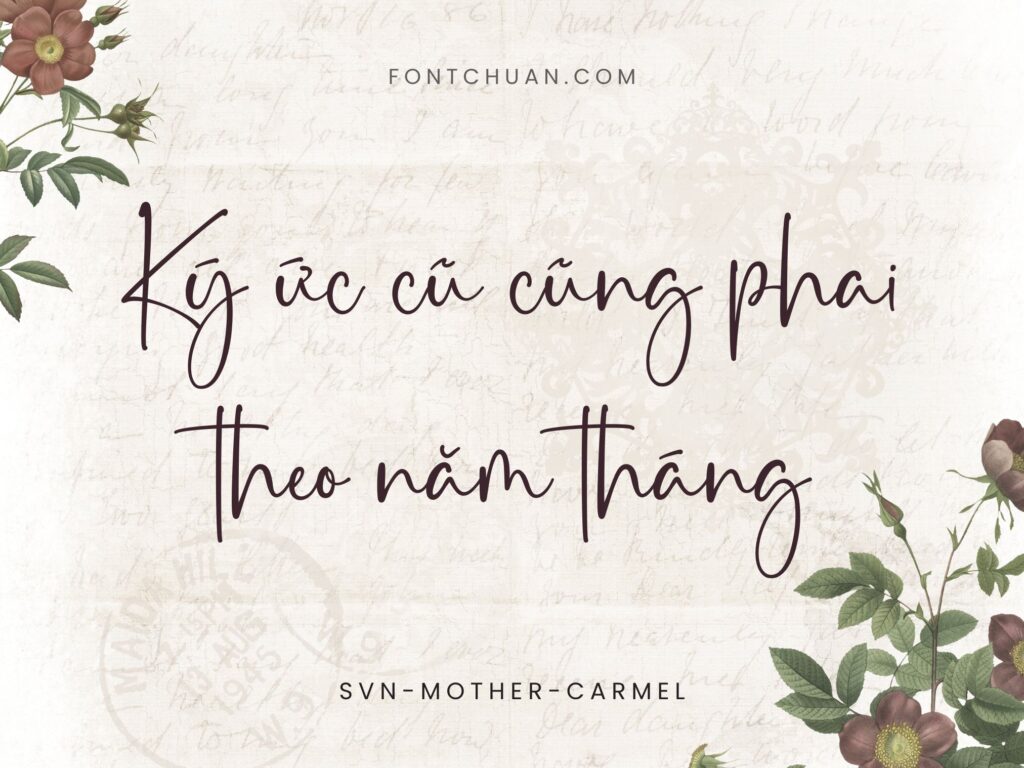
Font SVN Mother Carmel Việt Hóa
Tác giả Font: Rasditype
Font SVN Mother Carmel là phiên bản Việt hóa của kiểu chữ Mother Carmel, được thực hiện bởi STYLEno.1 Fonts. Mother Carmel là một font chữ script mang phong cách viết tay thanh lịch và tinh tế, được thiết kế với sự chăm chút tỉ mỉ, tạo nên vẻ đẹp mềm mại và quyến rũ. Font này được mã hóa PUA, cho phép truy cập đầy đủ vào tất cả các glyphs và swashes, giúp người dùng dễ dàng tạo ra các thiết kế độc đáo. Mother Carmel bao gồm đầy đủ các ký tự chữ hoa, chữ thường, chữ số và dấu câu, hỗ trợ đa ngôn ngữ. Font này phù hợp cho nhiều mục đích sử dụng khác nhau như thiết kế thiệp mời, logo, tiêu đề, bao bì sản phẩm và các ấn phẩm truyền thông.
SVN Mother Carmel lý tưởng cho các dự án thiết kế yêu cầu sự thanh lịch và nữ tính, như thiệp cưới, thiệp mời sự kiện, logo thương hiệu và các ấn phẩm truyền thông. Các ngành nghề như thiệp cưới, giáo dục và bất động sản có thể tận dụng font này để tạo điểm nhấn trong thiết kế. Ngoài ra, font cũng thích hợp cho các sự kiện như Tết, Valentine, Sinh nhật và các lễ hội khác.